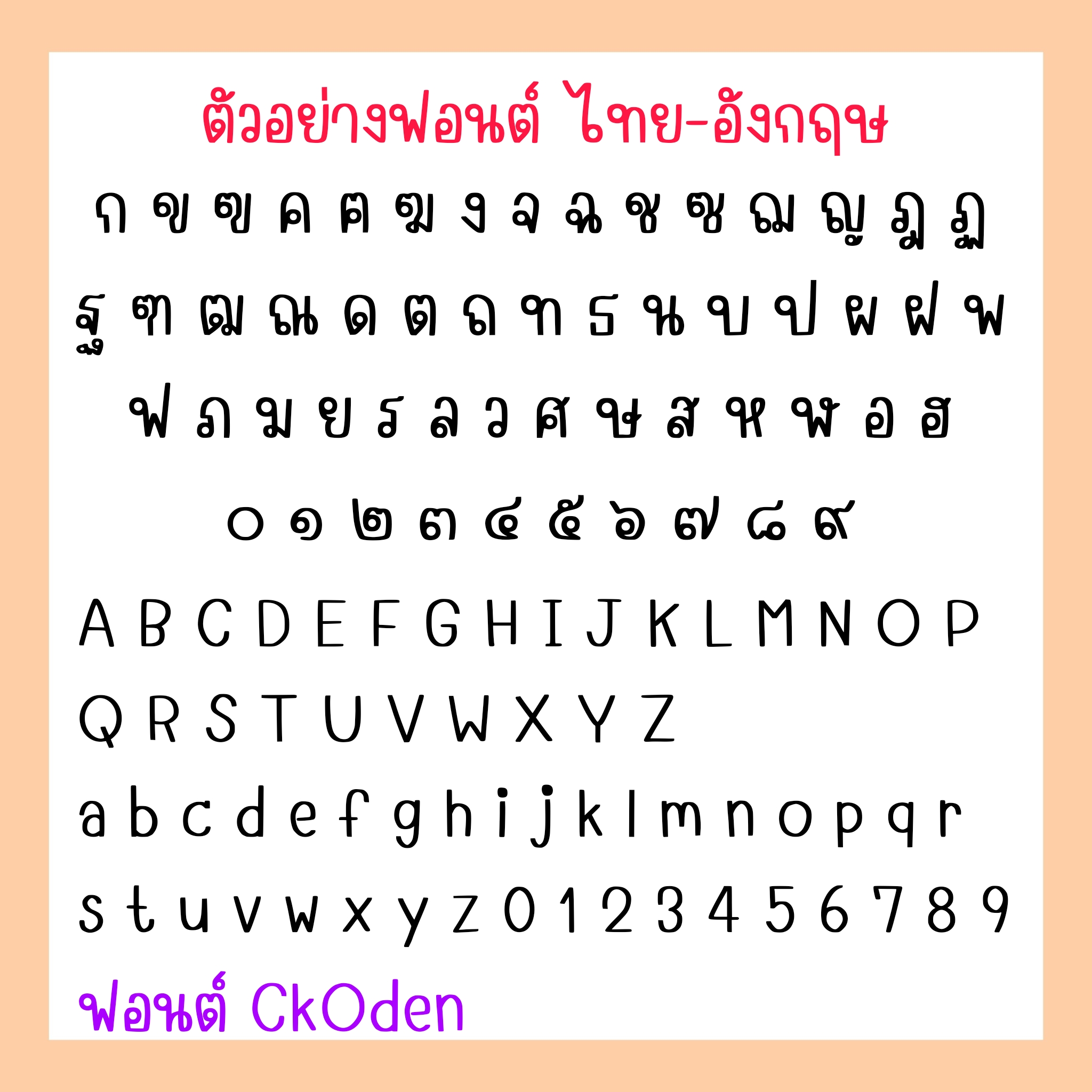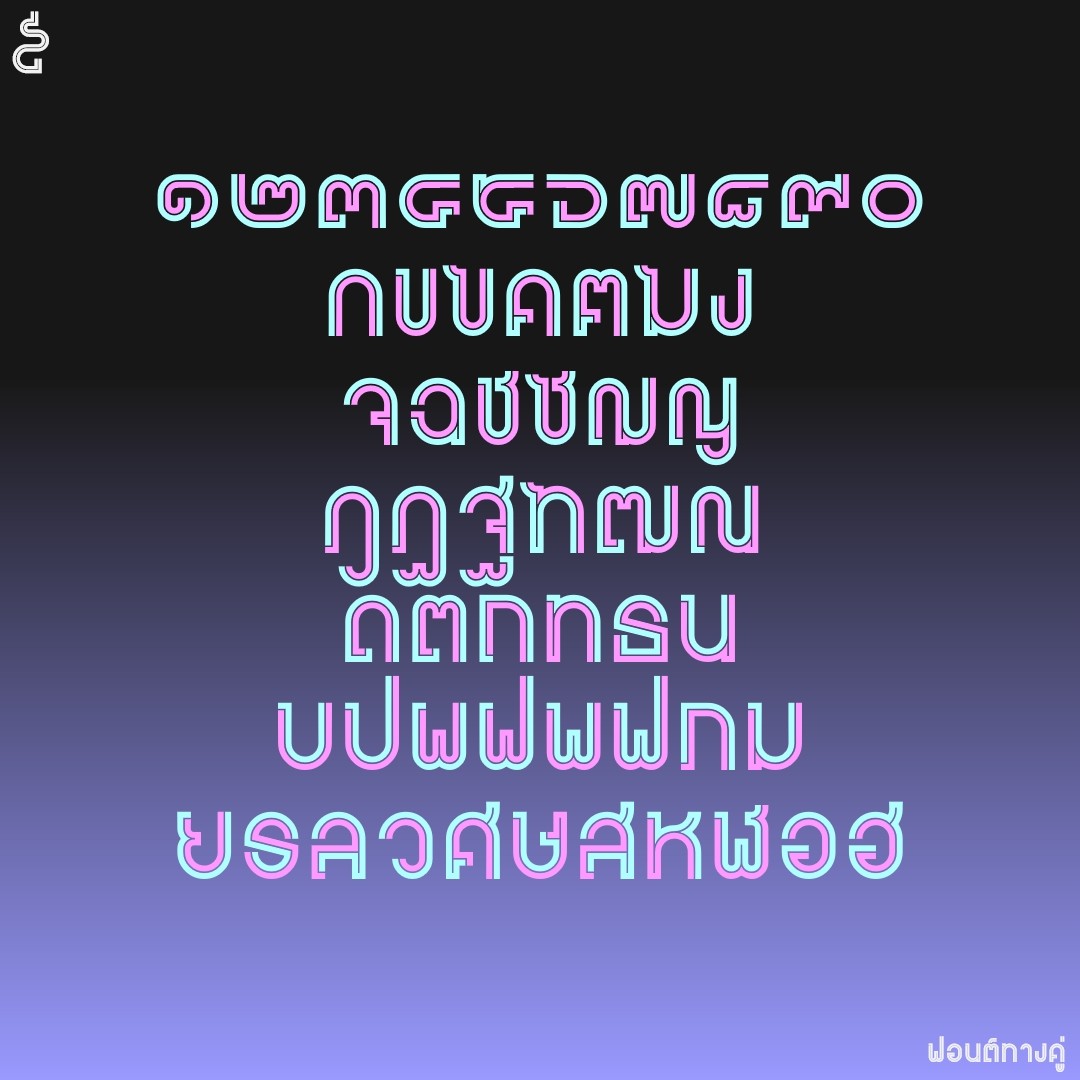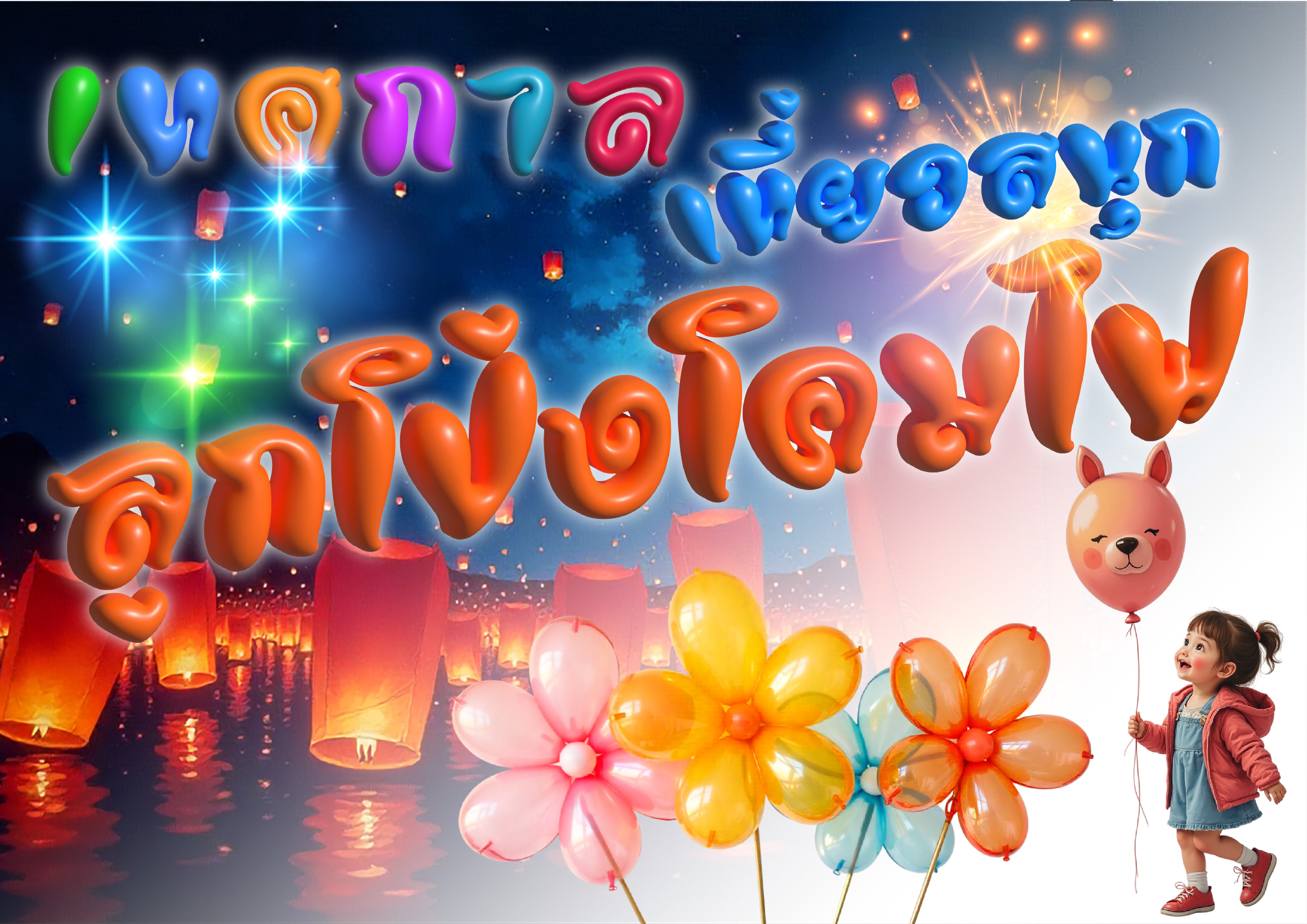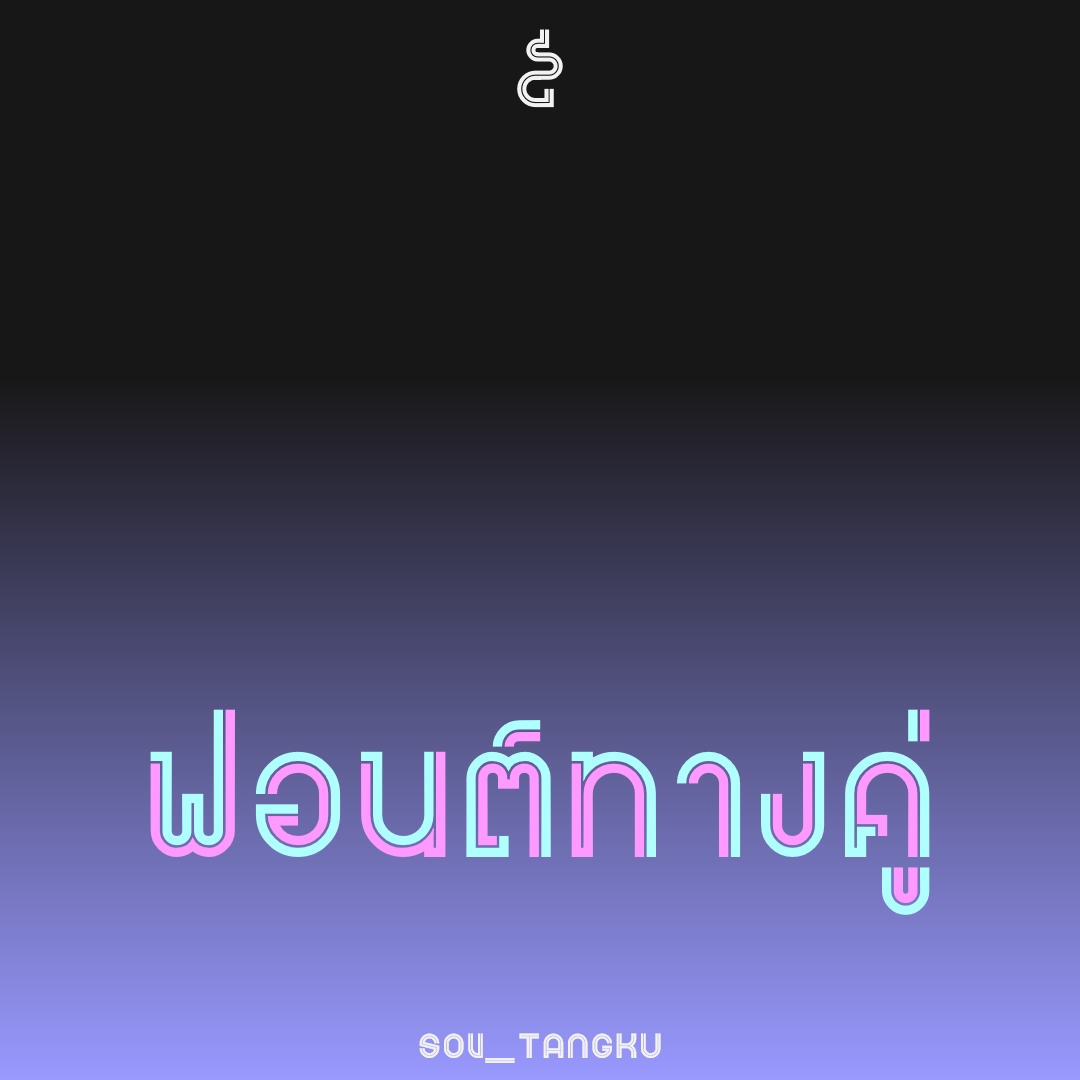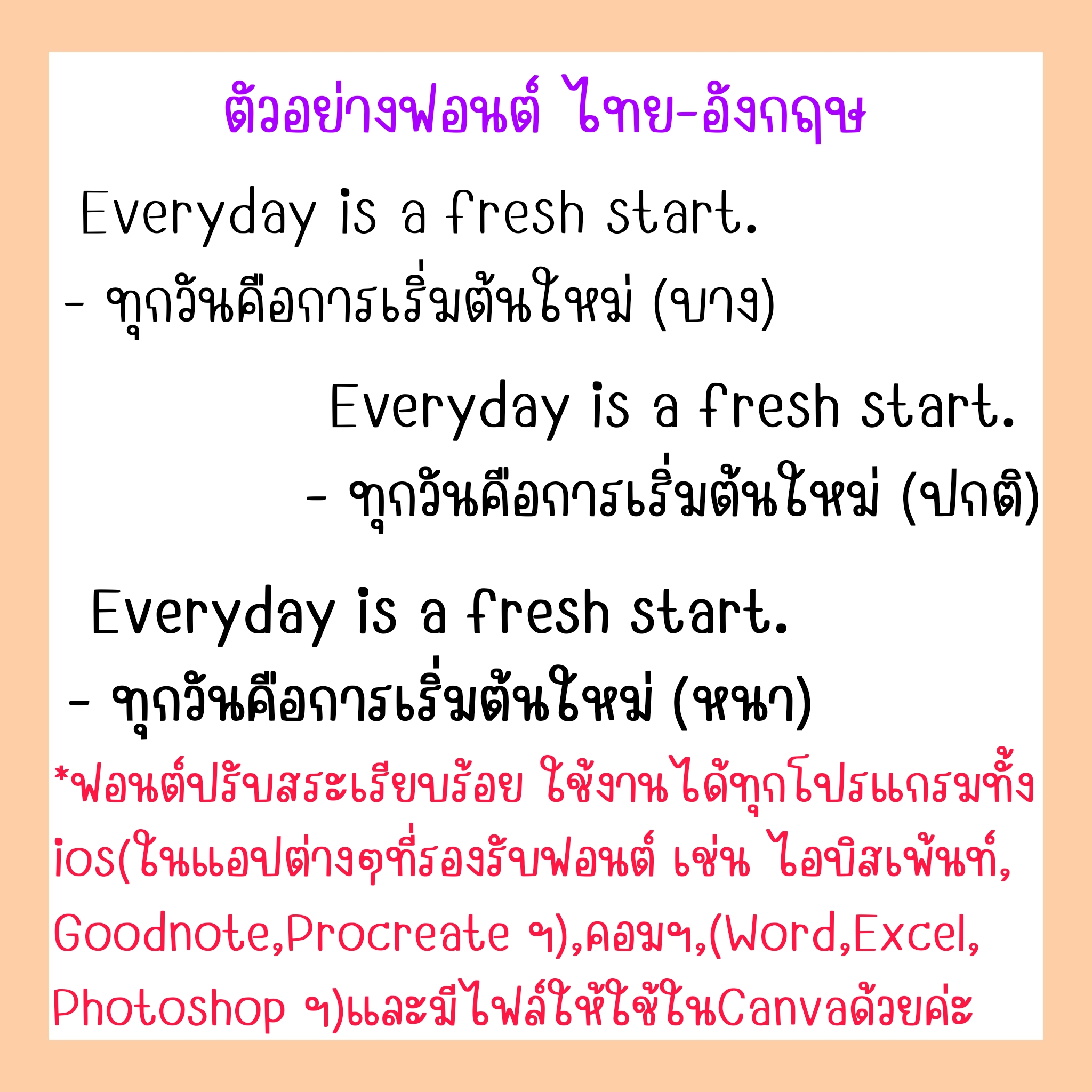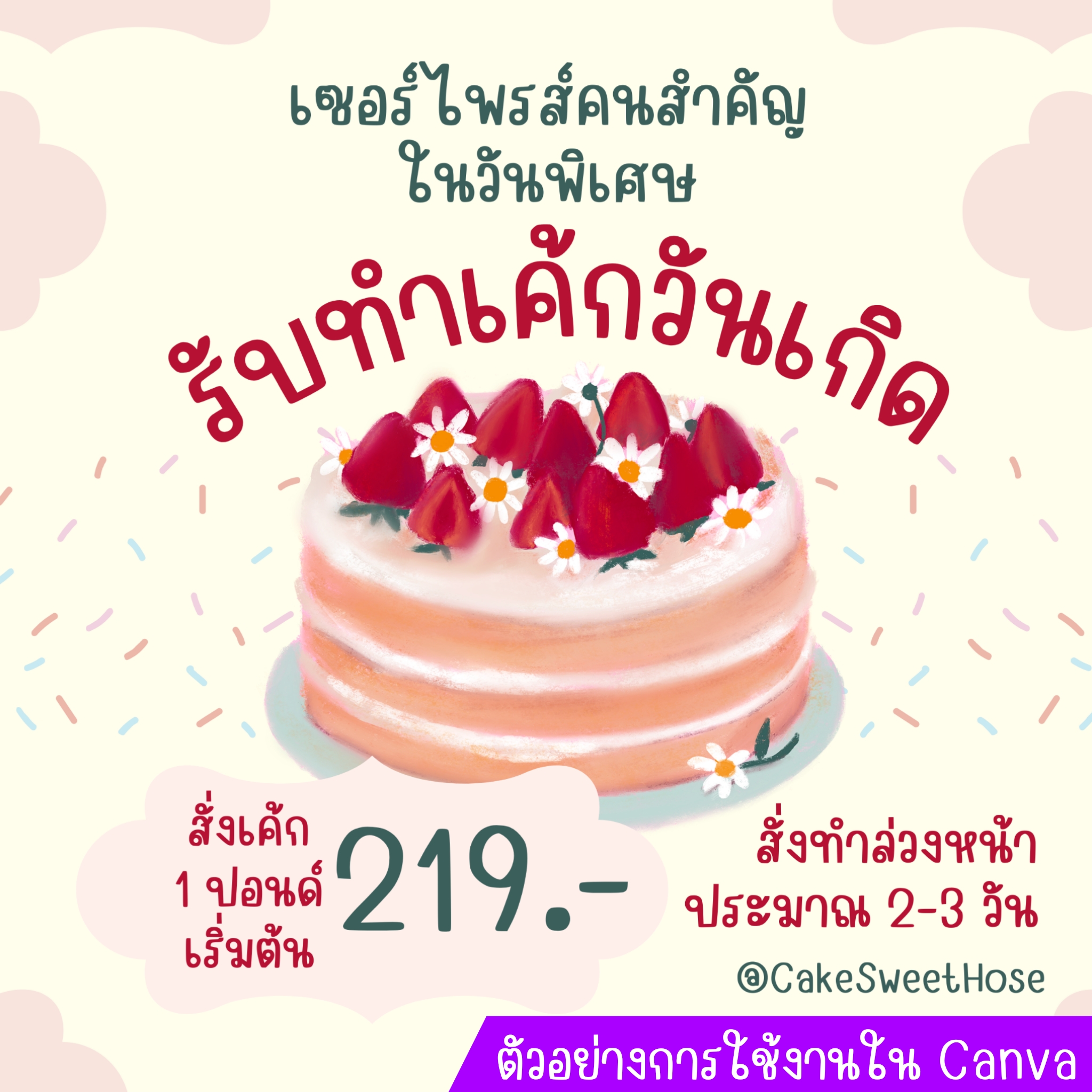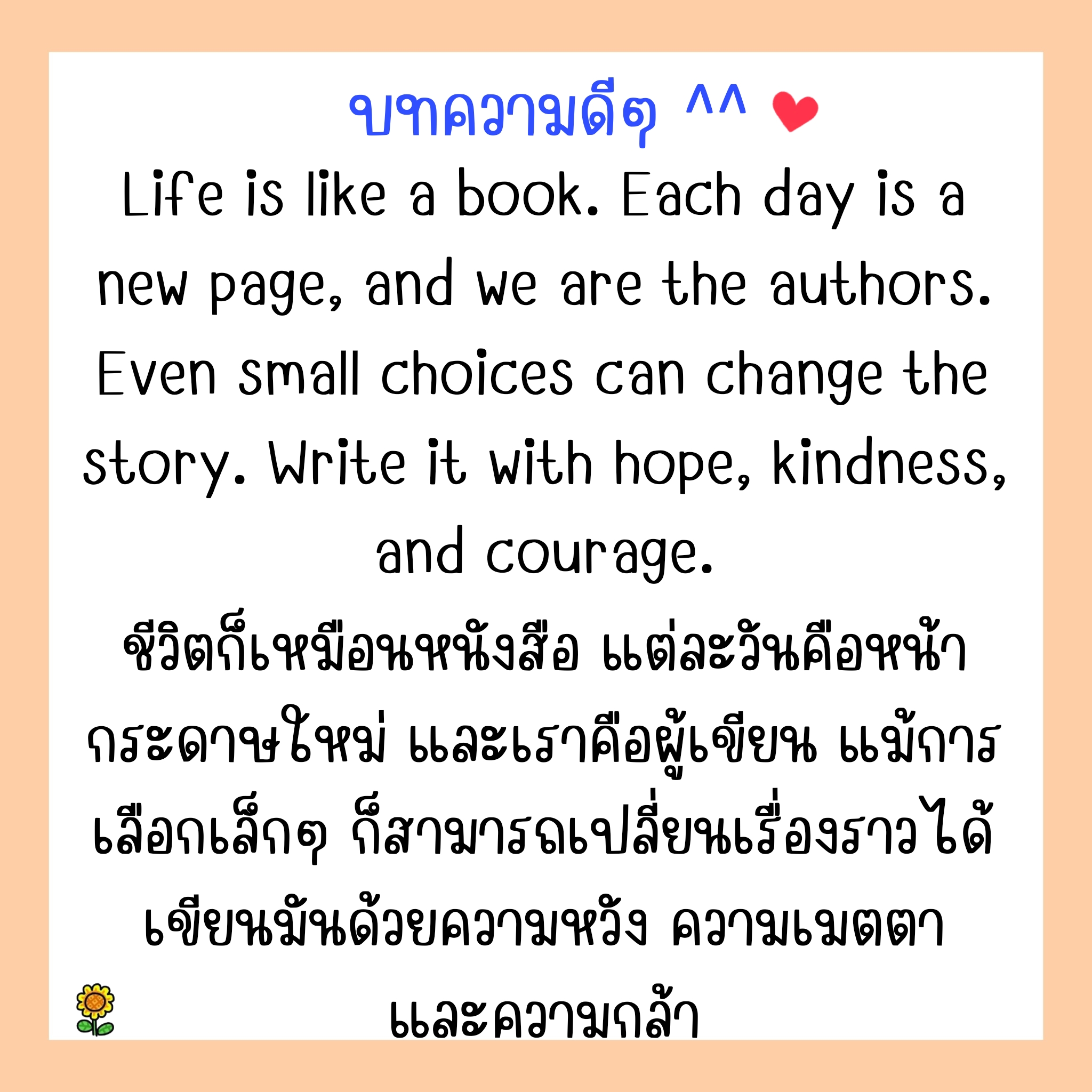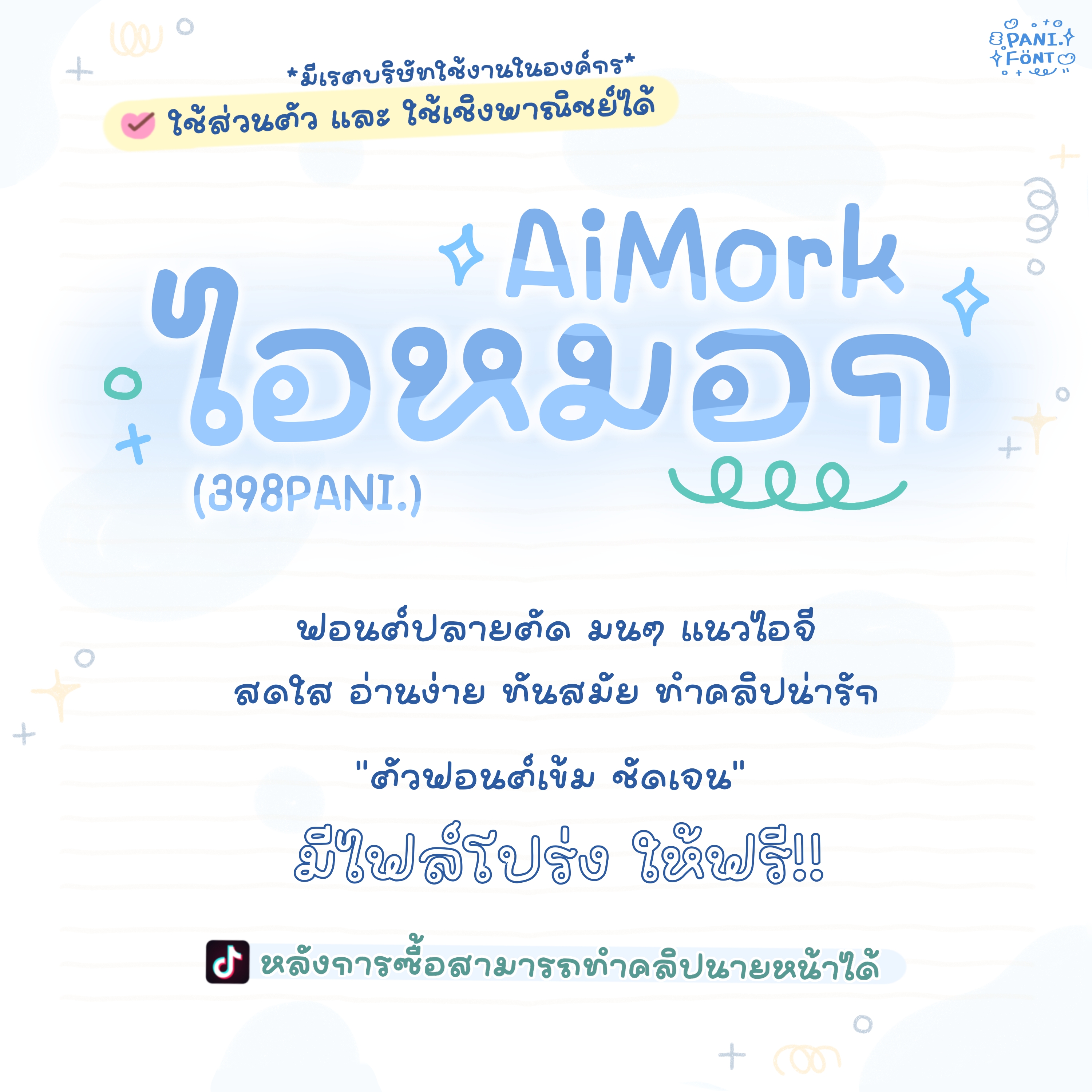
ชื่อฟอนต์ : ทางคู่
ฟอนต์ทางคู่ อักษรไทยไม่มีหัวแต่มีหัว ตัวเดียวแต่สองฟอนต์ ทำสองสีได้ เวลาใช้ยุ่งหน่อย ต้องซ้อนตัวปรกติ กับตัว bold
ชื่อฟอนต์ : :ซินนี่ฮ็อป (GMCfnZinnyhop)
ฟอนต์ เคอาร์ตไทยอีสาน (Kart-Thai Esan) เป็นฟอนต์ที่เขียนไว้เน้นใช้คุ้มๆกับทุกงานออกแบบป้าย+โลโก้ครับ #ฟอนต์อีสาน #ฟอนต์ลายมือ ฟอนต์นี้เป็นเดโม่ครับ สามารถใช้ครอบคลุมหลายโปรแกรมโหลดทดลองกับไอแพด และแอนดรอยด์ดูก่อนได้
- ฟอนต์ CkOden ฟอนต์ลายมือเส้นตัด แนวน่ารัก หัวกลมๆ อ่านง่ายค่ะ
ꔛฟอนต์  398PANI.ไอหมอก
ฟอนต์แนวไอจี ปลายตัด หัวกลม
ดูสบายตา เข้าใจง่าย ไม่ต้องแต่งเยอะ
ชื่อฟอนต์ : ลูนี่พัฟ (GMCfnLunipuff)
จองฮับ
ฟอนต์ลูกโป่ง
ปุ๊กลุก